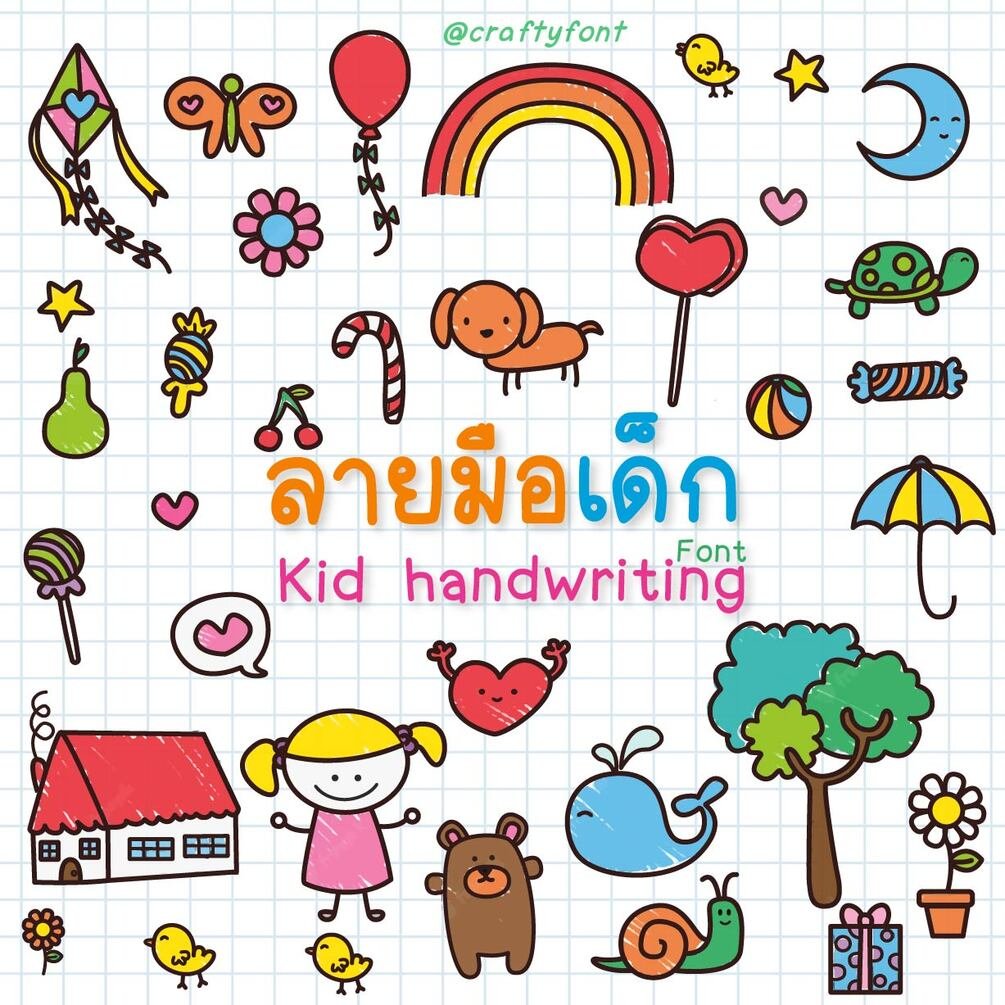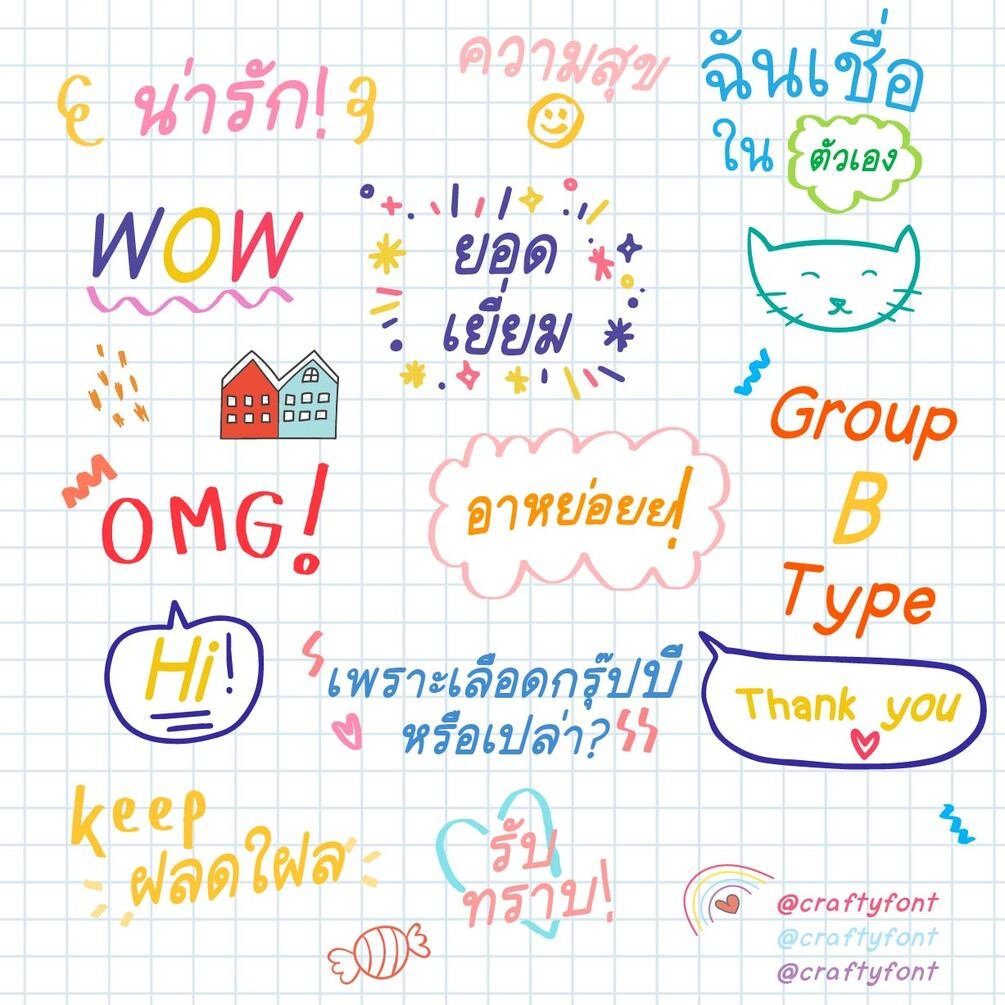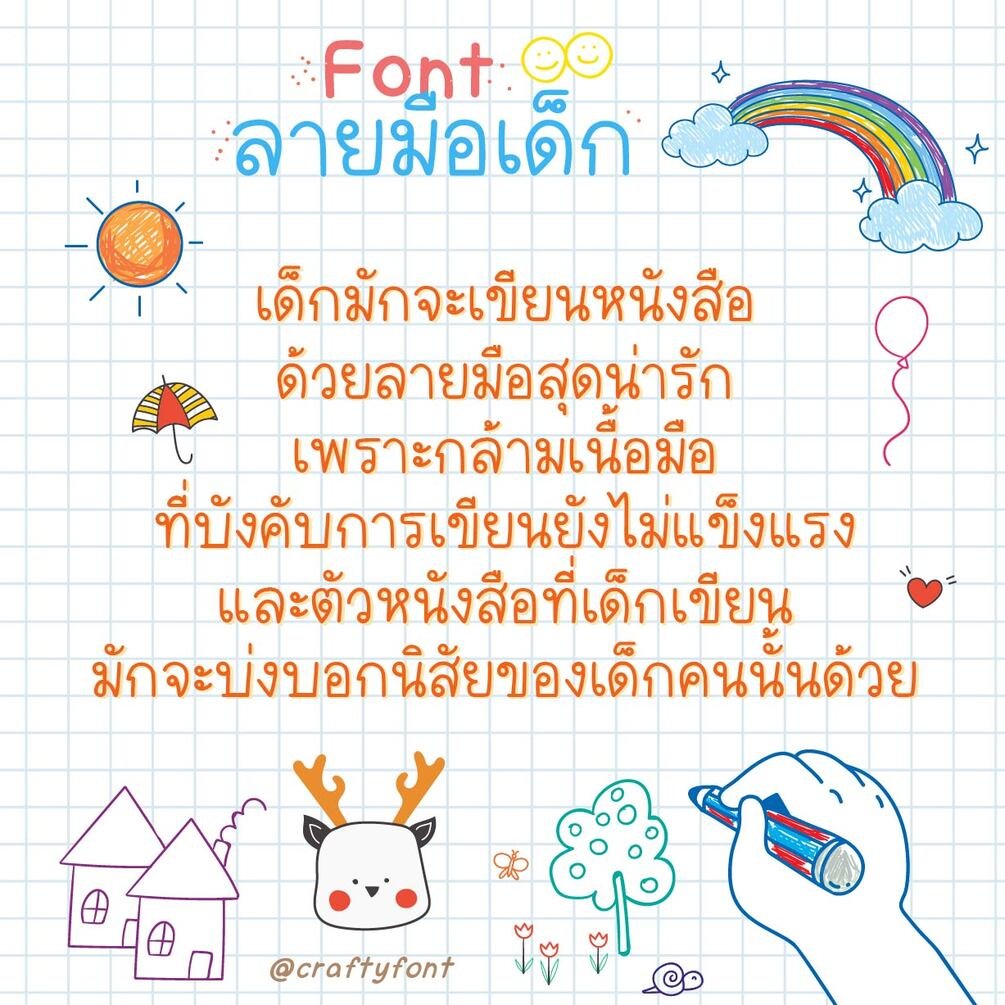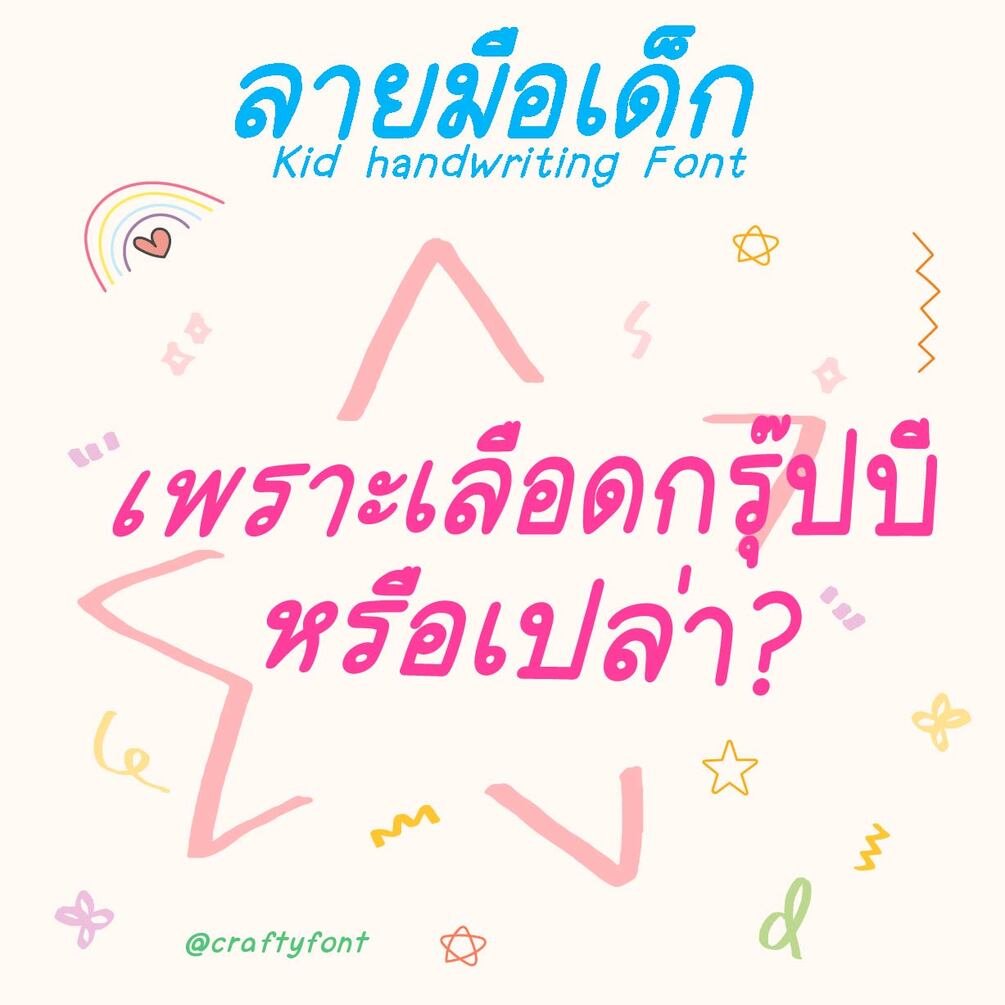
LaimueDek Font (ฟอนต์ลายมือเด็ก)
ฟอนต์ลายมือเด็ก เอาไว้เขียนโน้ต ทำสรุป สารพัดประโยชน์ เพราะน้องอ่านง่าย พาดหัวก็ดี เขียนเป็นเนื้อเรื่องก็อ่านง่าย แฟมิลี่ชุดนี้มีทั้งหมด 6 ตัวด้วยกัน ตัวหนา ตัวบาง ตัวปกติ และตัวเอนของแต่ละขนาด ฝากไว้ในอ้อมอกอ้อมใจพี่จ๋าด้วยนะจ๊ะ 🥰